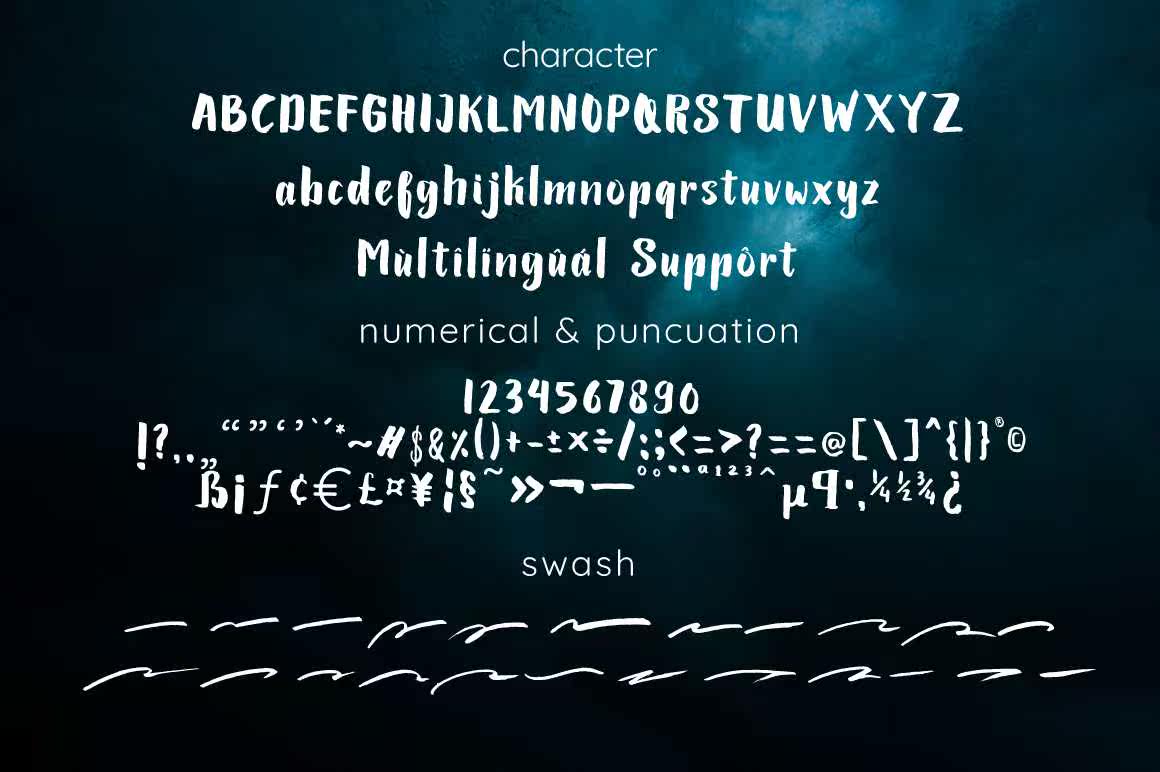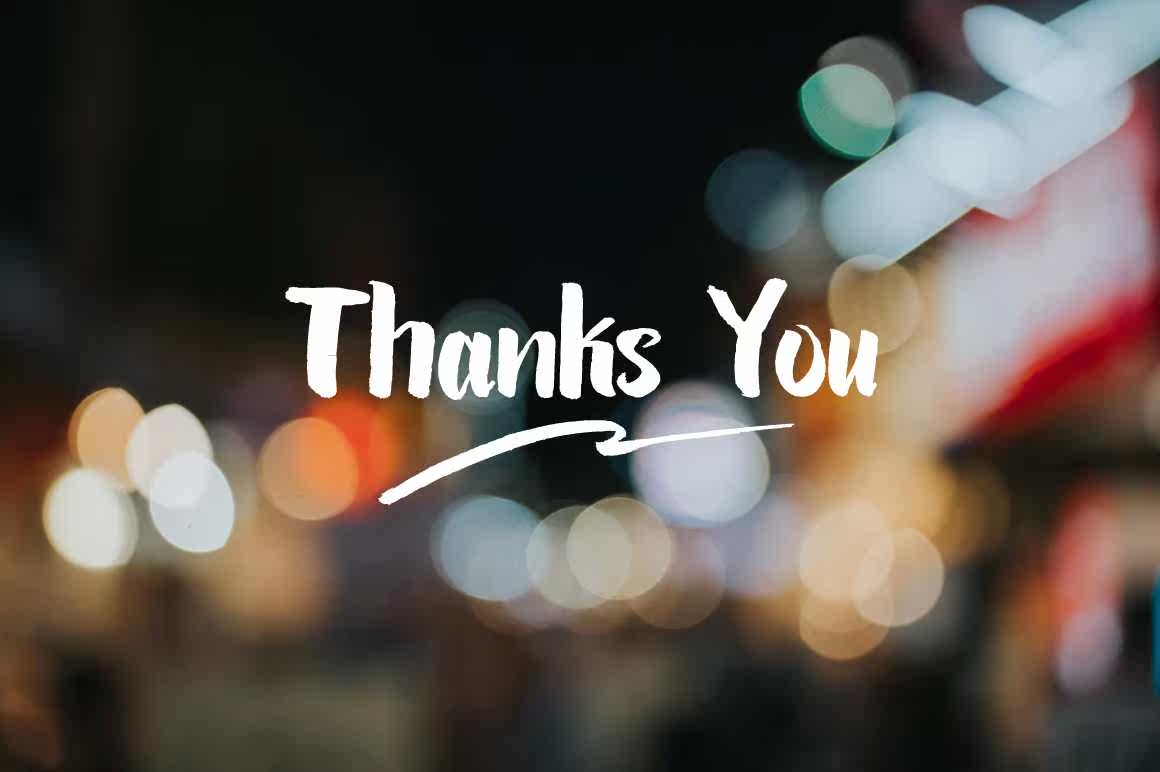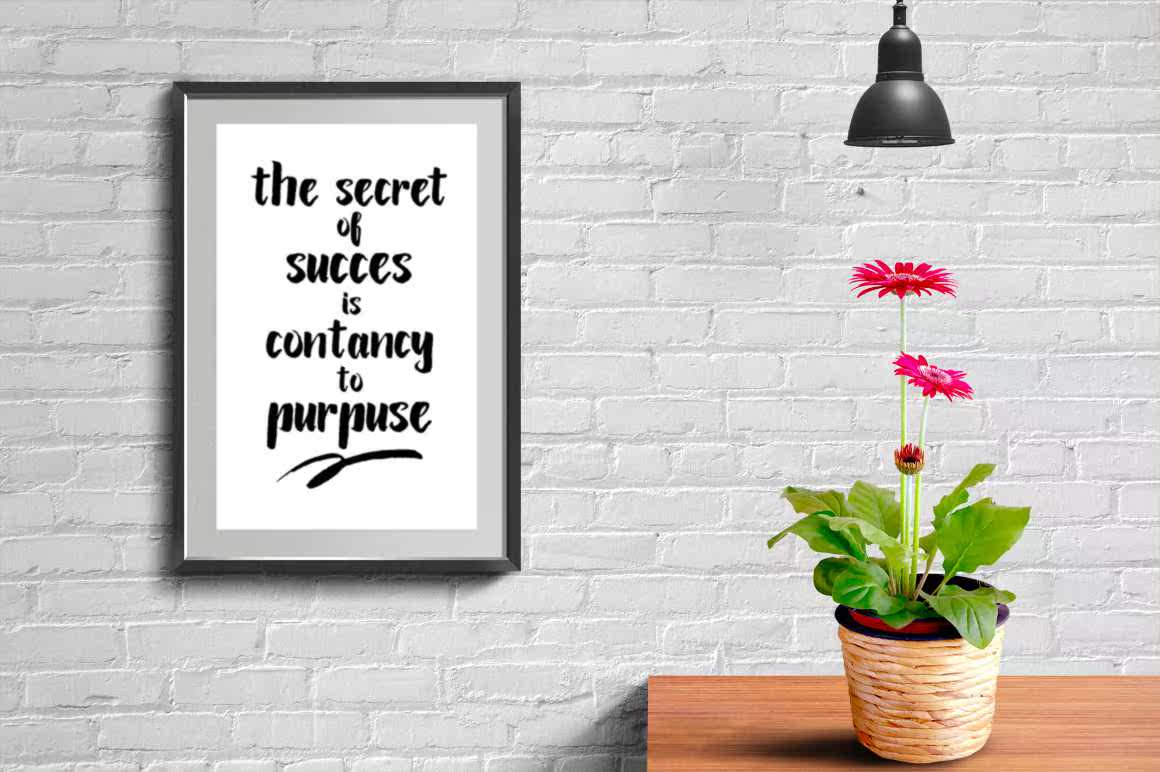
LARIESSACONTEMPORARY HAND-madebrushtype。它将为您提供设计风格的外观和感觉。LARIESSACONTEMPORY已涂漆未涂漆,并经过仔细的数字化和优化,以获得最佳设计效果。LARIESSACONTEMPORY HAND-madebrushtype。它将为您提供设计风格的外观和感觉。LARIESSACONTEMPORY已涂漆未涂漆,并经过仔细的数字化和优化,以获得最佳设计效果签名